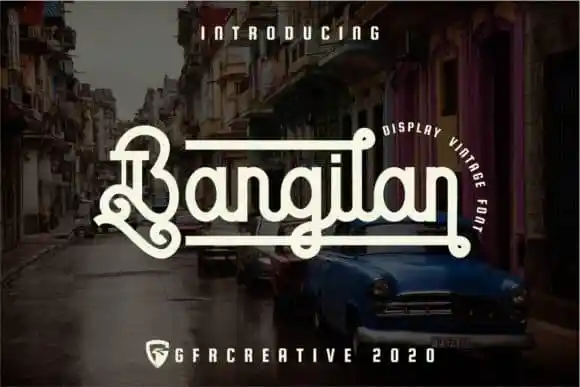
A Bangilan Display Font é uma opção perfeita para quem busca personalidade e destaque em projetos visuais. Criação do GFR Creative, inspirada nas antiguas panfletagens publicitárias que dominaram as ruas no início de nossas vidas urbanas. Esta tipografia monoline é ideal para elementos de marca, como logomarcas e rótulos, projetos visuais, headlines e materiais promocionais. A Bangilan Display se destaca em seu estilo forte e elegante, sendo especialmente atraente para aplicações em design vintage, desde roupas até rótulos de embalagens, fazendo deste um recurso indispensável para qualquer designer que busca adicionar um toque único à sua marca ou projeto. A fonte é perfeitamente adaptada para variados usos e gera resultados impressionantes em diversos formatos e tamanhos.